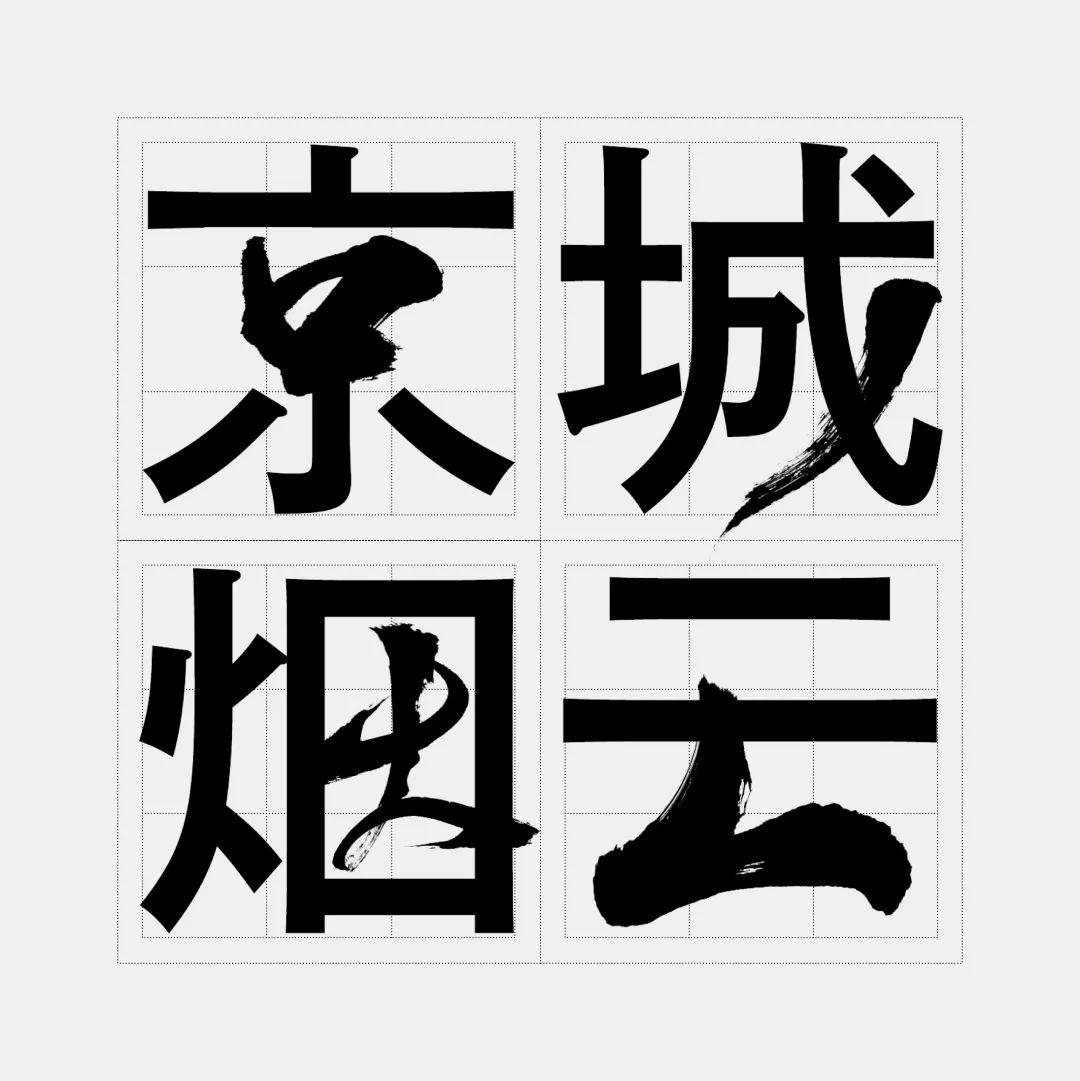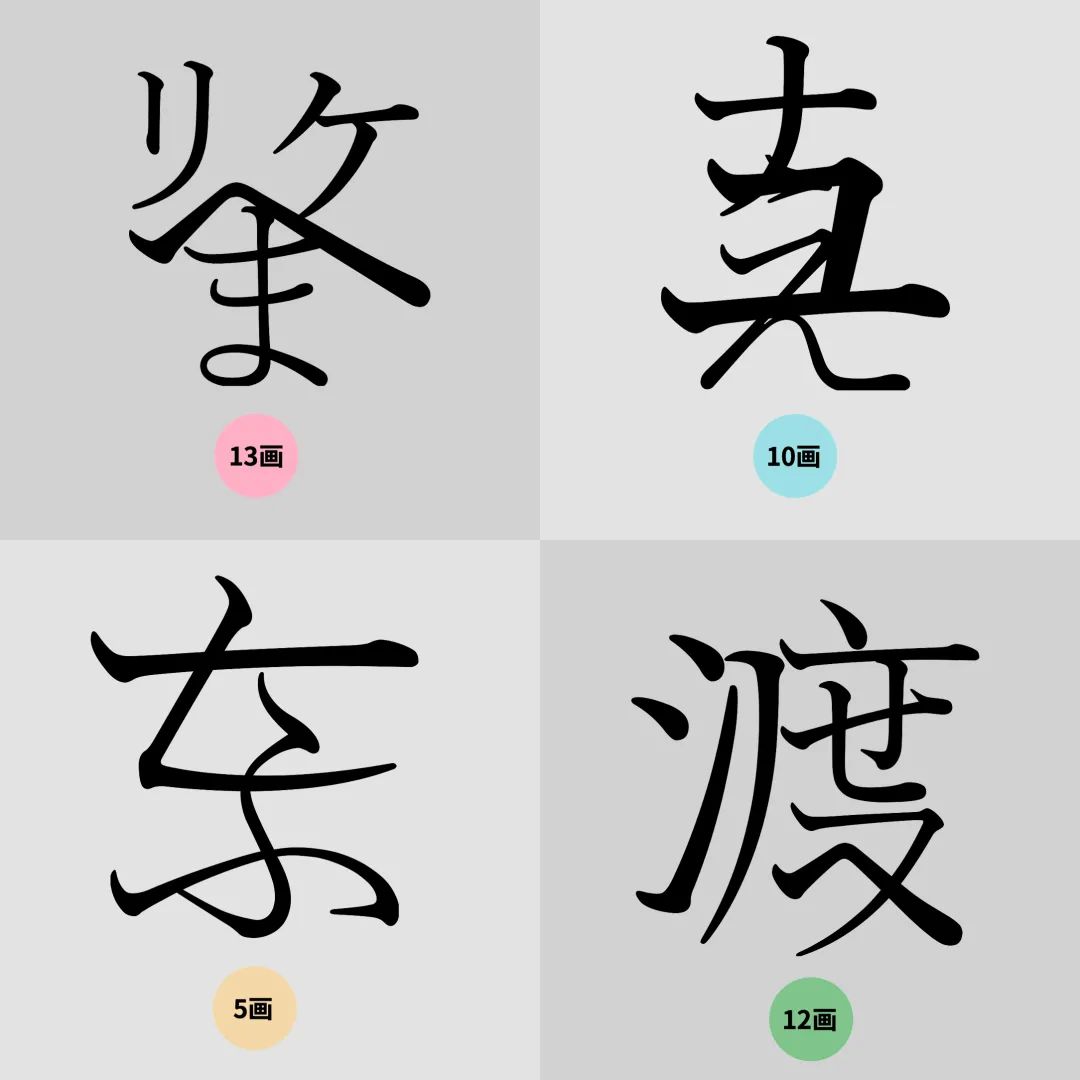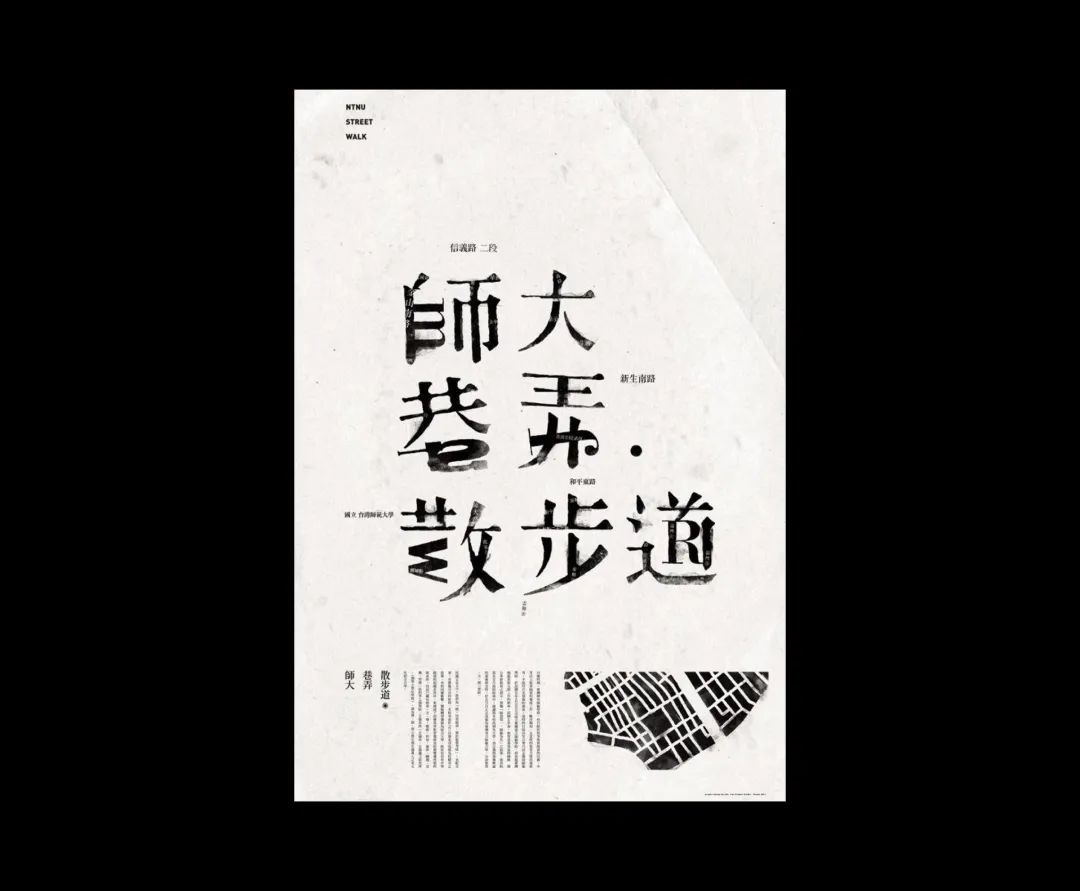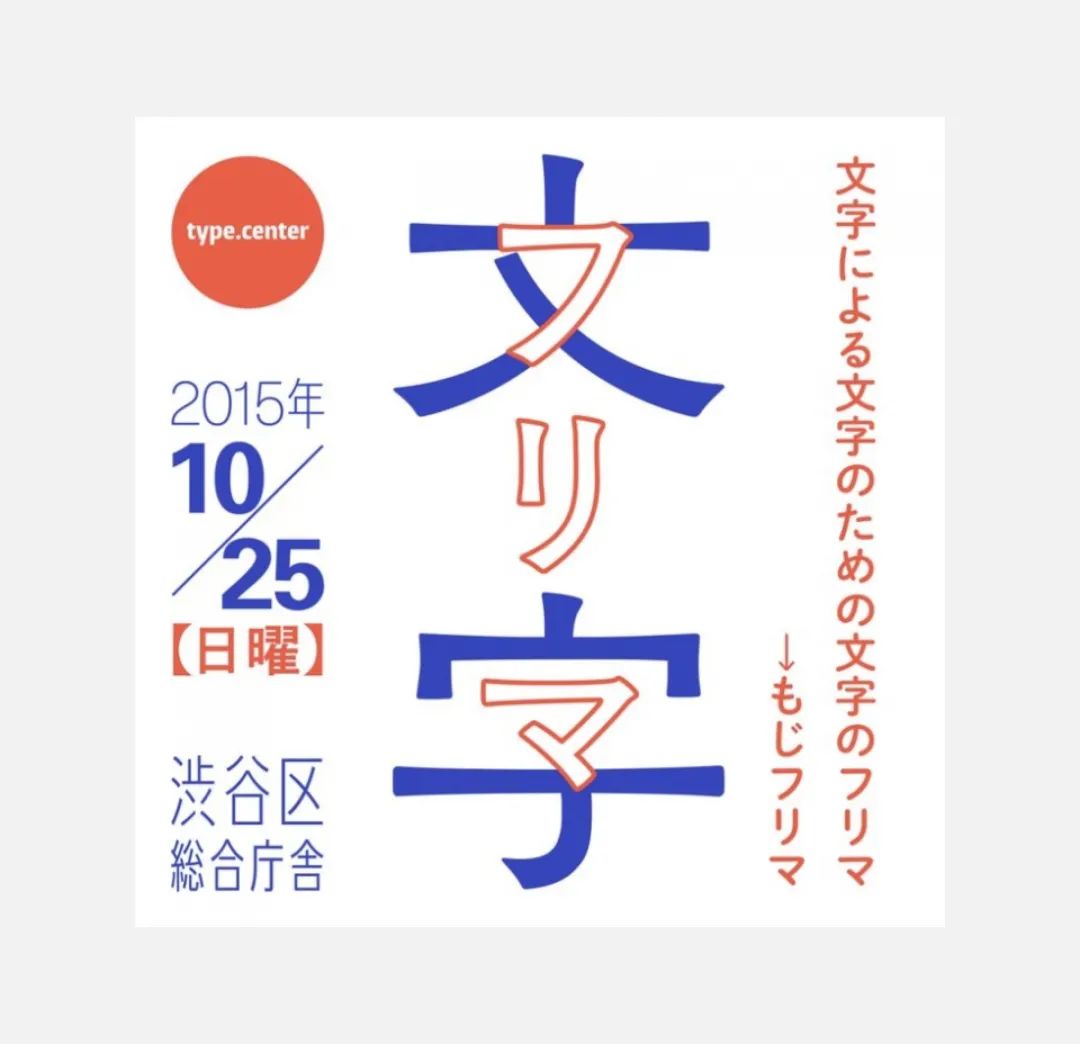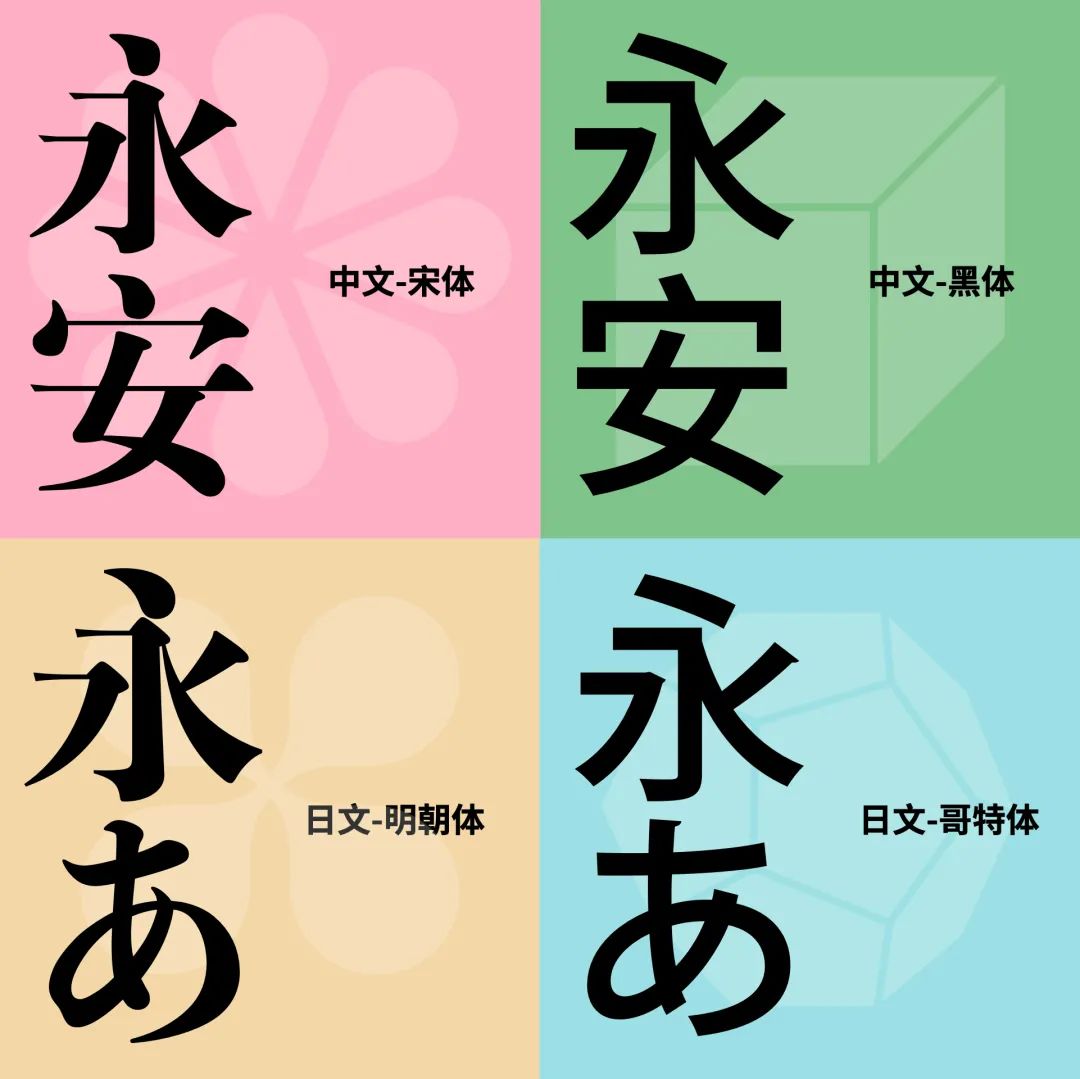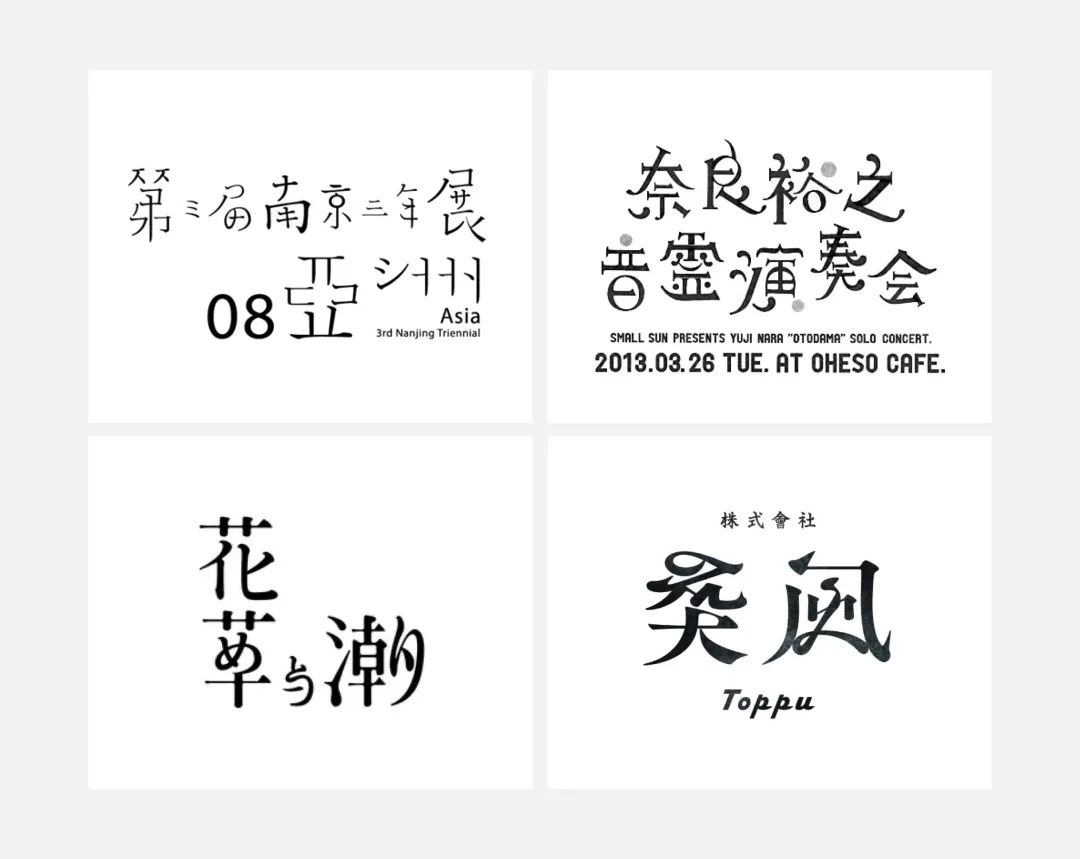
相信大家都碰到过这样的情况:有时候总感觉使用普通的字库字体表现力不够,完全进行字体设计又费时费力。其实这时候,我们完全可以采取一些相对简单又容易出效果的方法,而笔画置换法就是其中一种。使用这种手法,我们可以通过现成的字库字体来完成创作。即便没有成熟的字体设计技能,仍然具备很强的可操作性。
今天,主要给大家介绍的笔画置换思路分为三种,分别是借用西文字体、日文假名以及汉字书法来进行置换。当然,从本质上来说,它们都是在进行不同字体的拼接。下面,我们先来讲用西文字体替换的部分。
首先我们来简单看一下行业里大家是如何去做的。比如在这个作品中,就用到了多种西文字体来进行替换,来达到一个多种对比效果。其中,字母「m」「J」「R」使用了常规的衬线体,字母「S」使用了粗衬线体,这里的「S」是经过镜像翻的,另外还有字母「W」使用了无衬线体。而汉字的部分则统一是宋体。
不难看出,如果大家使用宋体为基底来进行与西文字体的置换,西文字体的选择范围还是比较广泛的,可以是衬线体、意大利体、粗衬线体、或是无衬线体等。这其实就与我们做版式设计时进行字体搭配的思路是一样的。那么根据这样的推断,我们不难想象,对于以黑体为基底的汉字来说,同样也可以搭配这几种相应的西文字体类型。
至于究竟选择哪一种,还得看我们具体想呈现出怎样的视觉印象。并且从制作难度的角度来考虑的话,字体间的对比越大,一定是越难把握的。
所以从最简单和容易出效果的角度出发,我们更推荐大家这四种搭配方式,分别是宋体与衬线体,宋体与意大利体,黑体与粗衬线体,以及黑体与无衬线体。
而再回过头来看这些作品,这一回我们不看字体搭配,转而观察西文字体在置换时出现的频次。
可以看到,基本上同一个汉字,最多只会置换一次完整的西文单字,这样既能保持良好的识别度,也不会有太高的制作难度。
当然,如果能力足够,也是可以同时使用多个字符来进行置换,但是这无疑已经超过今天我们要探讨的范围了。
下面我们也来应用一下这个方法制作一个简单的案例。大家也可以找来一个合适的文案进行自我练习,比如这里我选择使用「梦幻岛」这三个字。
首先要过的第一关当然是汉字字体的选择了,毕竟西文字体也是根据汉字的字体类型来搭配选择的。对于梦幻岛这三个字,显然宋体字会更加满足我们对「梦幻」二字的想象。
当然,如果再精益求精一些,我们还需要进而选择一款更加贴切的宋体,比如这里第一款,边边角角过于简洁,直来直去,并不够梦幻;而第二款笔画虽然足够圆润,但是结构太过紧缩,古典意味明显,也不在考虑范围内;第三款宋体不仅结构足够开阔,横竖笔画对比明显、转角还有圆角的处理,整体更有一种若即若离的梦幻感。所以我们这里选择使用第三款宋体。
选好字体以后,就可以逐一对单字「做手术」了,我们需要找到汉字中可以被替换成英文的部分,并完成替换。
比如在这里「梦」字上方的两个木字形部件中,我们以找到近似于大写英文字母「T」的部分,这时候就可以直接把「T」拿过来尝试替换。但是把 T 放大到合适的粗细时,整体就太大了,这时候我们只需要对字母进行一个笔画长短上的调整即可。
第二个「幻」字,最明显又容易改动的地方当属右边横折钩了。这里竖钩的造型一下就能让我们联想到英文字母中的「J」,因为刚才我们已经使用了大写字母来作为替换,所以出于统一性的考虑,我们依旧使用大写的「J」来替换。可以看到,替换之后整体依然显得十分和谐,甚至如果让一个不太懂宋体构成的朋友来看,估计都挺难发现其中的奥妙。
接着,我们来看最后一个「岛」字,繁体的「岛」字整个上半部分由大量的横竖画组成,并且一体感较强,想要对这部分动手还需要多加斟酌,所以下半部分的山字才是我们的第一目标。
在大写字母中,恰好有字母「E」能与汉字的「山」在字形上有所呼应,只需要将「E」逆时针旋转九十度就可以做到。
直接将「E」替换掉原本的部件,当然这里面我们还需要像之前的「梦」字那里一样,去简单调整一下「E」字的比例关系,让它能够被安放在这样一个小的空间里。
这就是我们在最短时间内修改好的三个字,这一次的尝试整体更加保守一些,虽然对汉字的结构做到了尽可能的保留来满足辨识度,但是整体太过呆板,缺乏了一些中西合璧所应具备的亮眼之处。所以我们可以选择重头再来一遍,看看有没有更好的处理思路。
这一次我们可以尝试对下面的夕字进行替换,从整体来看,能与夕字在外形扯上关系的只有意大利体中的大写 A 了。
然而当我们尝试替换以后,不难发现,虽然识别度勉强过得去,但是更强烈的感觉还是替换得太过僵硬,上下的统一感有所欠缺。除非我们是自己有意想营造这种感觉,不然就显得很应付。
并且本身意大利体的标准模式该是小写才对,所以我们这里直接把选择范围再一次缩小,这一次的替换我们只是用小写的意大利体。而在这样的范围下,能和「夕」字扯上关系的字母就完全没有了。
所以我们减少需要被替换的范围,去掉中间的一点,只保留一个外框,我们可以在脑海中复现一下外框的笔顺,加上外框的造型,很容易让我们联想到小写意大利体的「n」。
替换过后,可以发现不仅不会影响字形的正常识别,并且意大利体自身的手写感也充满了一种微妙的感觉,非常容易衬托出字义的氛围。当然,我们还需要继续对「n」进行一个粗细上的调整,让它更加融于整个字形之中。
接着来看「幻」字,置换的部分这次我们依然选择竖钩的部分,而所替换的字母还是选择「j」,毕竟没有比这俩兄弟更适合互相转化的组合了。不过因为意大利体本身就具备倾斜的属性,所以在拼接的时候没有办法放在一个最满意的位置,比如右上角的地方难免有些超出了原本的字面大小。本着只做微调的出发点,这里我们就不对「j」进行倾斜角度上的调整了,而是适当延长原本汉字上面的一横,让他们相交而成为一个整体。拼好后的字虽然易于辨识,但是难免有些小问题,这个我们之后再统一解决。
最后一个岛字,依然替换下面的山字部件,不过这一次我们不可能再使用大写的 E 来完成拼接了。往后依次查找,可以看到小写的 m 似乎是一个可行的替换方案。不过,m 的开口朝向和山字完全相反,这里我们选择把字母旋转 180 度来让 m 的开口朝向变为上方。适当调整文字,让它看起来和山字部件差不多大小即可。
另外还可以使用字母「w」来替换,过程和「m」相似,不再赘述。直接对比两种方案,显然是「w」的方案更胜一筹,左边「m」因为经过旋转,整体的书写流畅度看起来差了许多,并且原本旋转前的起笔处与「岛」的勾画相冲突,只能避让开,而右边「w」方案就不会有这样的问题出现。所以我们选择后者。
现在我们把三个字放在一起观察,不难看出原本单字看起来还可以的造型,当它们组合在一起后,就显得有些歪歪扭扭了,并且负空间也有一些小问题不太好解决。如果大家不具备字体设计的能力,去过分调整笔画就不是一个可行的路数,应该怎么办呢?
既然西文部分选用了意大利体,那么汉字部分我们也可以选择倾斜一定的角度来形成一致的动势,这样不但是单字本身,字与字之间也显得更加统一和谐。
这样我们的西文字体置换汉字笔画的小案例就大致完成了。
最后可以配上一定的文字与装饰元素,进一步烘托氛围。总的来说这样的方法还是考察大家的观察能力与联想能力,执行起来并不具备很高的难度,只需要会基本的软件操作就能完成,并且能在短时间内完成且具备不错的效果,性价比极高。
第二部分我们尝试将日文假名与汉字相结合。接下来,我们将把从构思到执行、从遇到问题到修改问题的整个过程完整呈现给大家。
我们先来对比一下,日文和中文都有哪些相同点和不同之处。首先,我们会发现,在日文里面是存在汉字的,虽然它们的写法和我们的简体字不太一样,但我们也能很直观的认出它们。
其次,日文中除了汉字之外还存在假名。也就是我们画面里现在标注着蓝色的部分。它们才是日文中最有代表性的符号,也是我们区别日文和中文的最直观的手段。
在简单对比日文和中文之间的差异后,我们就需要思考,应该如何将汉字与假名巧妙地结合在一起。
我们大致上有两个方向可以选择,首先就是中日互译,使用具有相同含义的汉字和假名去相互结合。
如果你选择了这条道路,那么恭喜你了,开局基本上就进入了「地狱模式」。由于这种设计形式对内容本身有苛刻的要求,所以并不常见。我们现在看到的这个案例,其实也只是把一句话中的汉字和假名部分做了一个结合。
所以,第二个方向在这样的衬托下,就显得难度没有那么高了。我们可以任意选择词组,然后搭配整个假名列表。在选择性增多的同时,也让组合的难度降低了很多。
接下来,我们一起来看看方向二能够给我带来什么样的视觉效果。作为以汉字为母语的我们来说,其实对它本身的样貌早就司空见惯了对吧?所以,当假名的笔画混入其中的时候,就会带来一种既熟悉又陌生的特性。在实现的难度上也不会太高。
我们都知道,常用的中文字体可以被分成宋体和黑体这两大类别。
而相对于中文的宋体和黑体,在日文中,也分别对应有明朝体和哥特体。如果说结构被替换的部分是一种写法上的对比,那么抵消这种不和谐的有效办法,就是选择风格相近的文字造形了。
如果感到费解,大家不妨试着思考一下:不同风格和造型的帽子,是不是也对应的不同的适用场景呢?
就像我们现在看到的画面一样,我们可以把帽子想象成是不同字体的造型。
如果一顶造形风格鲜明的帽子,出现在了错误的场景,就会变的很不合适。同样的道理,字型和其承载的信息就是这样的关系。